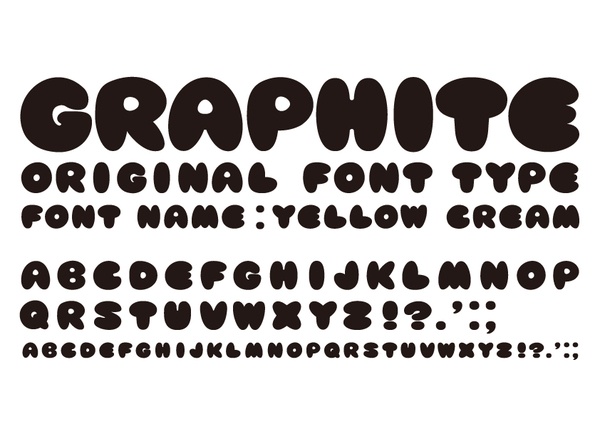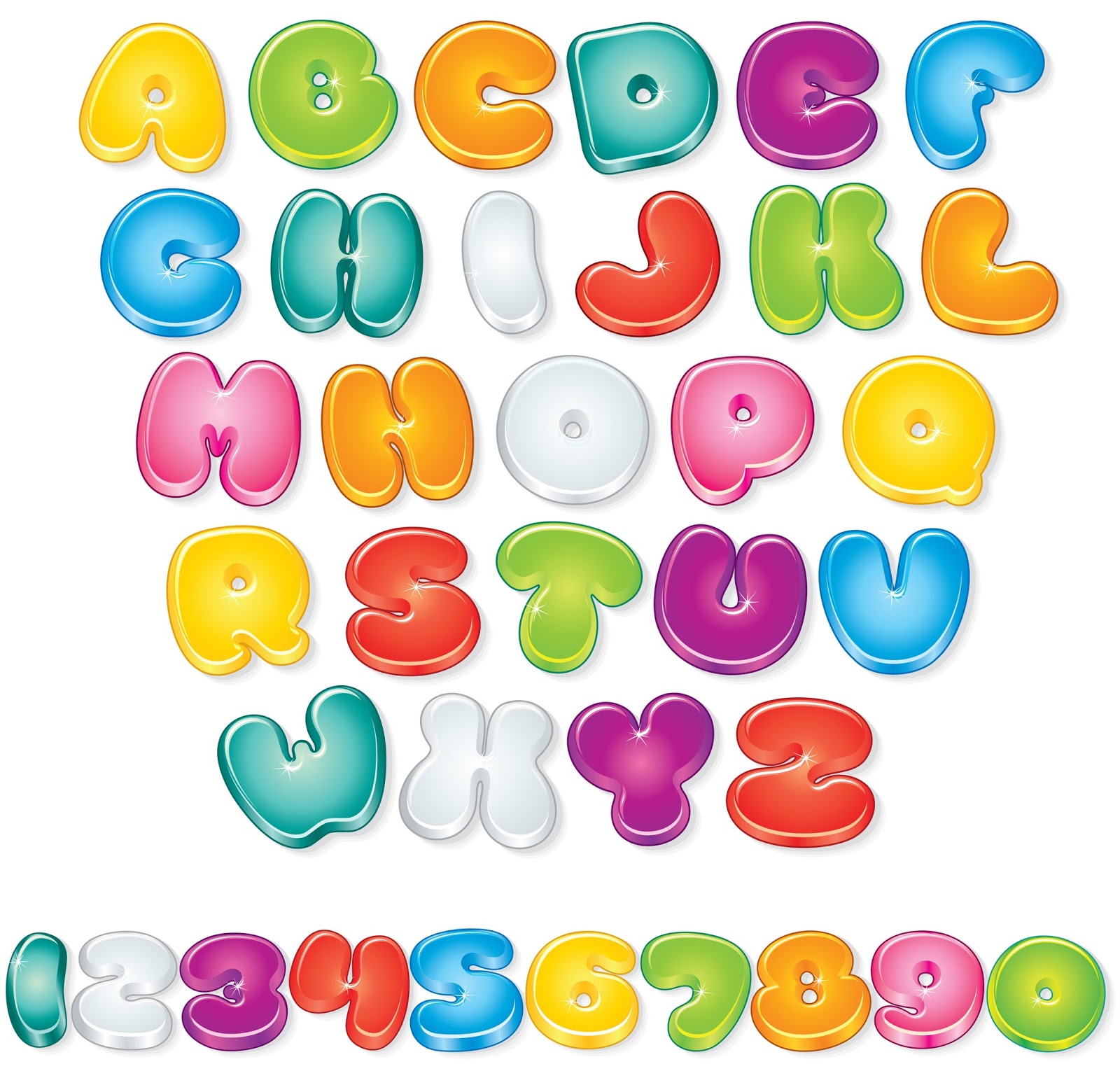
Создание шрифта в Photoshop
Шаг 7: Сложный N
Закругление двух оставшихся углов на N немного неудобно из-за полученной формы. Вам просто нужно делать это на глаз, округляя до тех пор, пока он не будет выглядеть правильно — не перетаскивайте слишком далеко, иначе диагональный штрих будет выглядеть совершенно неправильно.